今回は、AXIS Font* が使用されている書籍をまとめてご紹介します。 *一部調整されている文字も含みます。
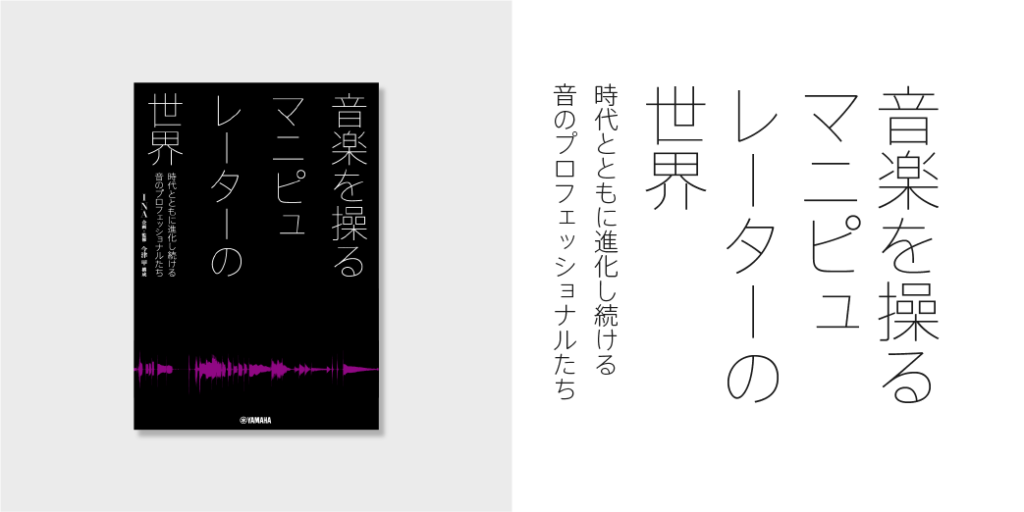
「音楽を操る マニピュレーターの世界 時代とともに進化し続ける音のプロフェッショナルたち」
企画・監修:INA
取材・構成:今津甲
発行:ヤマハミュージックエンタテイメントホールディングス
『大きなサイズで活躍する極細日本語フォント』
音楽の分野でのマニピュレーターについての書籍のタイトルとサブタイトルにAXIS Font ベーシックが使われています。
知的でデジタルな世界観に、極細の白抜き文字が新鮮な印象を与えてくれます。
極細の UL をサポートするウエイトとして開発された EL をサブタイトルに使って、上手くウエイトの印象を合わせています。
タイトル:AXIS Font ベーシック UL
サブタイトル:AXIS Font ベーシック EL
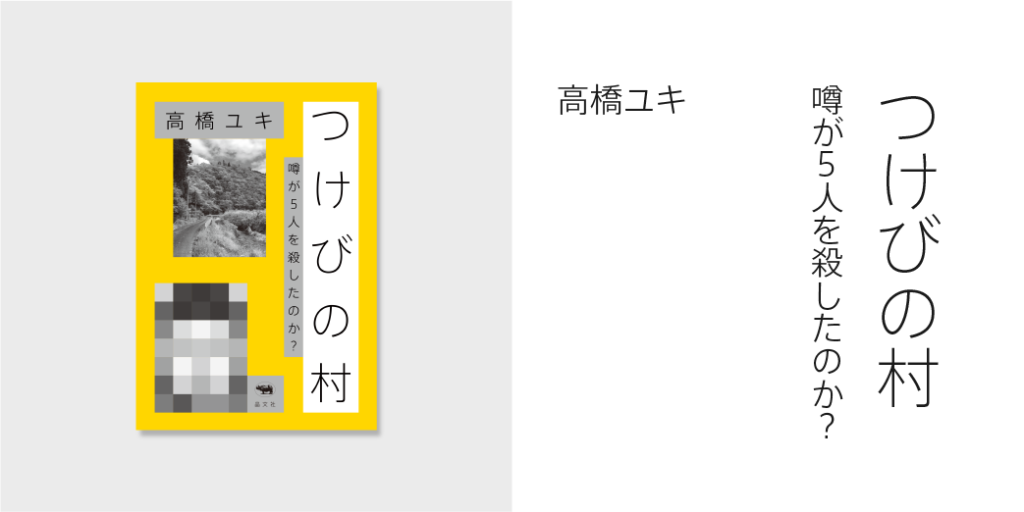
「つけびの村 噂が5人を殺したのか?」
著者:高橋ユキ
発行:晶文社
『白地が活きるデザイン』
連続放火殺人事件を追ったノンフィクション作品のタイトルとサブタイトル、著者名にAXIS Font ベーシックが使われています。
謎解きのための手掛かりをコラージュしたようなデザインに、白地を活かした文字組がモダンで知的な雰囲気を醸し出しています。
タイトル:AXIS Font ベーシック EL
サブタイトル:AXIS Font ベーシック L
著者名:AXIS Font ベーシック L
「ぼくにはこれしかなかった。」
著者:早坂大輔
発行:木楽舎
『中性的なサンセリフ書体』
地方都市で本屋を営む店主が綴るエッセイ集のタイトルと著者名にAXIS Font ベーシックが使われています。
シンプルな形の中に手書きのニュアンスを残した中性的な文字を使って組まれた平仮名だけのタイトルと、やさしい素朴なイラストレーションが絵本のような親しみやすさを感じさせてくれます。
タイトル:AXIS Font ベーシック B
著者名:AXIS Font ベーシック B
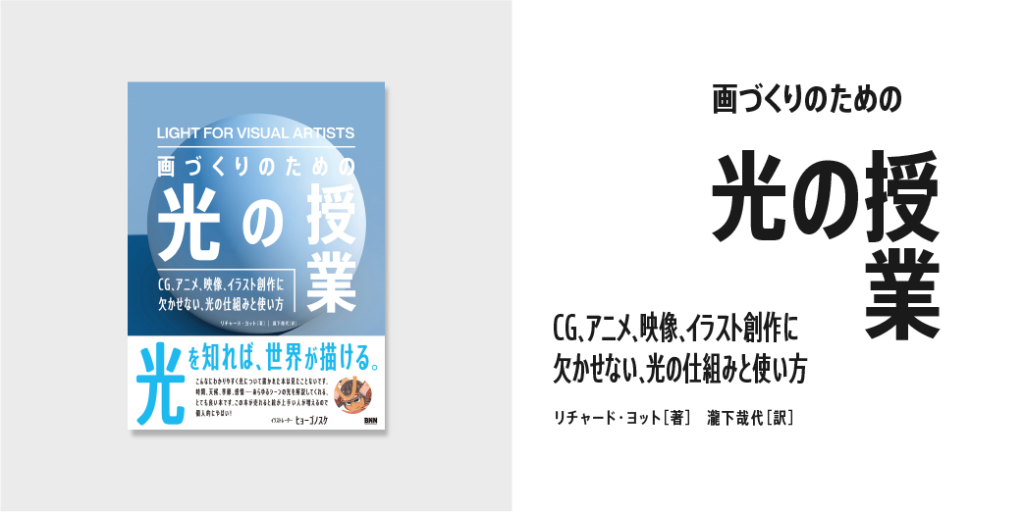
「画づくりのための光の授業 CG、アニメ、映像、イラスト創作に欠かせない、光の仕組みと使い方」
著者:リチャード・ヨット
翻訳:瀧下哉代
発行:ビー・エヌ・エヌ新社
『限られたスペースでも美しく余裕のある文字組』
光についての基礎知識と活用方法を解説した書籍のタイトルとサブタイトル、著者名など全面に AXIS Font コンデンス、コンプレスが使われています。
限られたスペースでの情報のメリハリに、長体フォントが活躍しています。
タイトルの「光の授業」がとても象徴的に目に飛び込んできます。
ちなみに帯には、AXISラウンド 50 コンプレス が使われています。さらに限られたスペースで効率的にこの書籍の魅力を伝えています。
タイトル:AXIS Font コンデンス B
サブタイトル:AXIS Font コンプレス M
著者名:AXIS Font コンデンス M
帯:AXISラウンド 50 コンプレス M